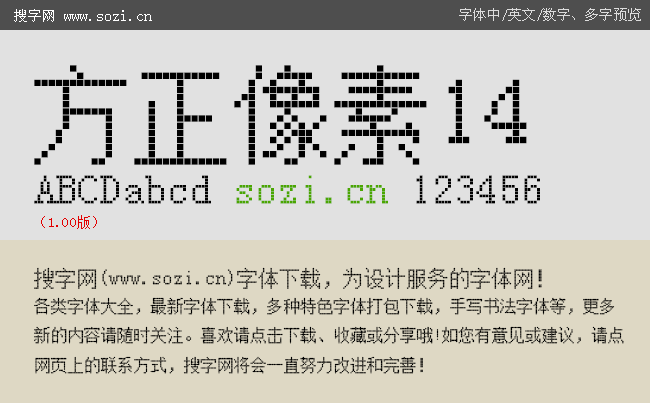
方正像素14
搜字網(wǎng)提供一款方正像素14中文字體下載,方正像素字體由正方形像素點(diǎn)組成的基于黑體、宋體基本字形的一套字體系列。方正像素體具有規(guī)范、工整,容易辨認(rèn)的特點(diǎn),適用于LED屏等電子屏幕,在易識(shí)的同時(shí),體現(xiàn)科技感和現(xiàn)代感。適合書(shū)籍設(shè)計(jì)、展板設(shè)計(jì)、海報(bào)設(shè)計(jì)等廣告設(shè)計(jì)場(chǎng)合使用。